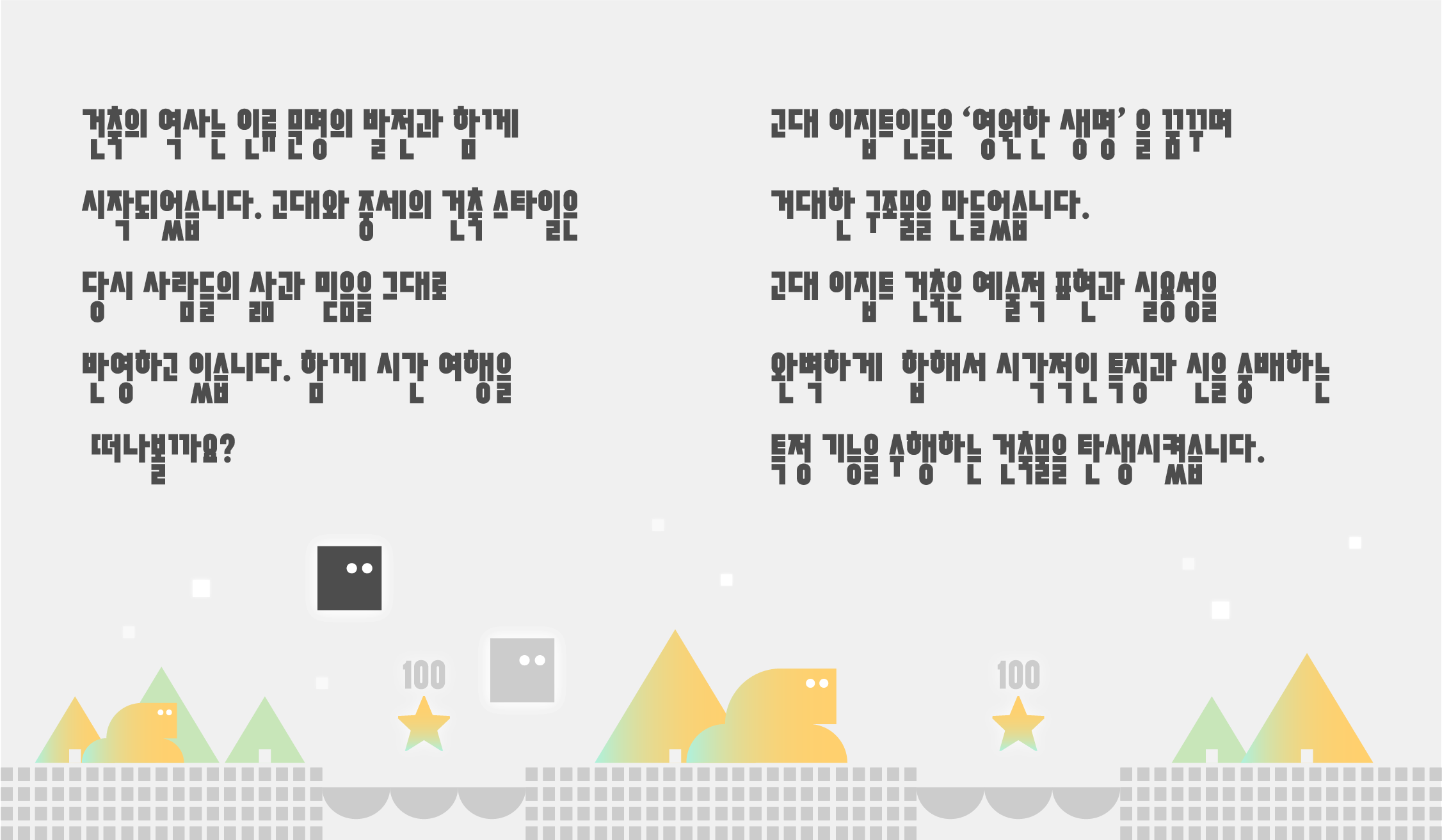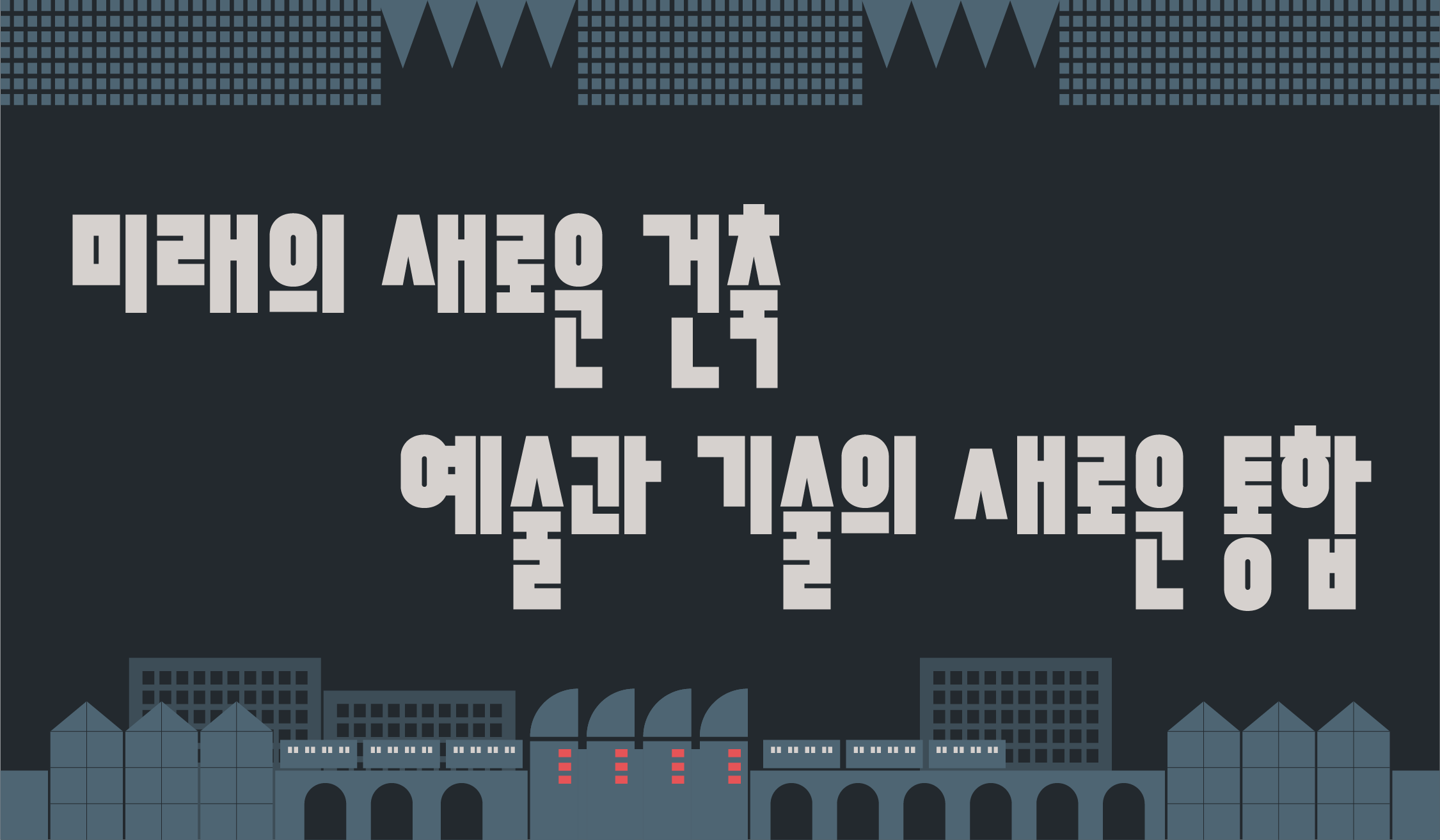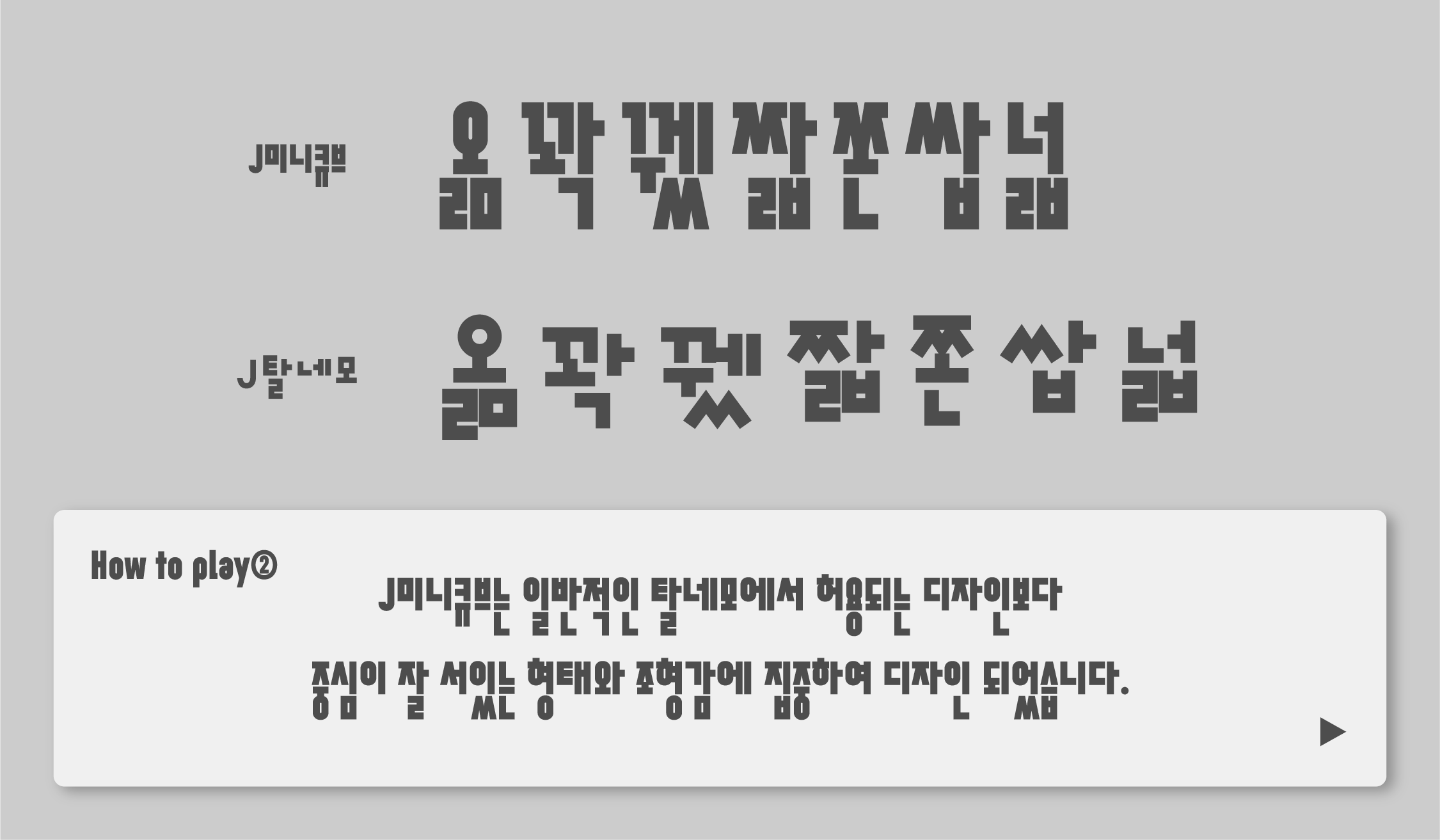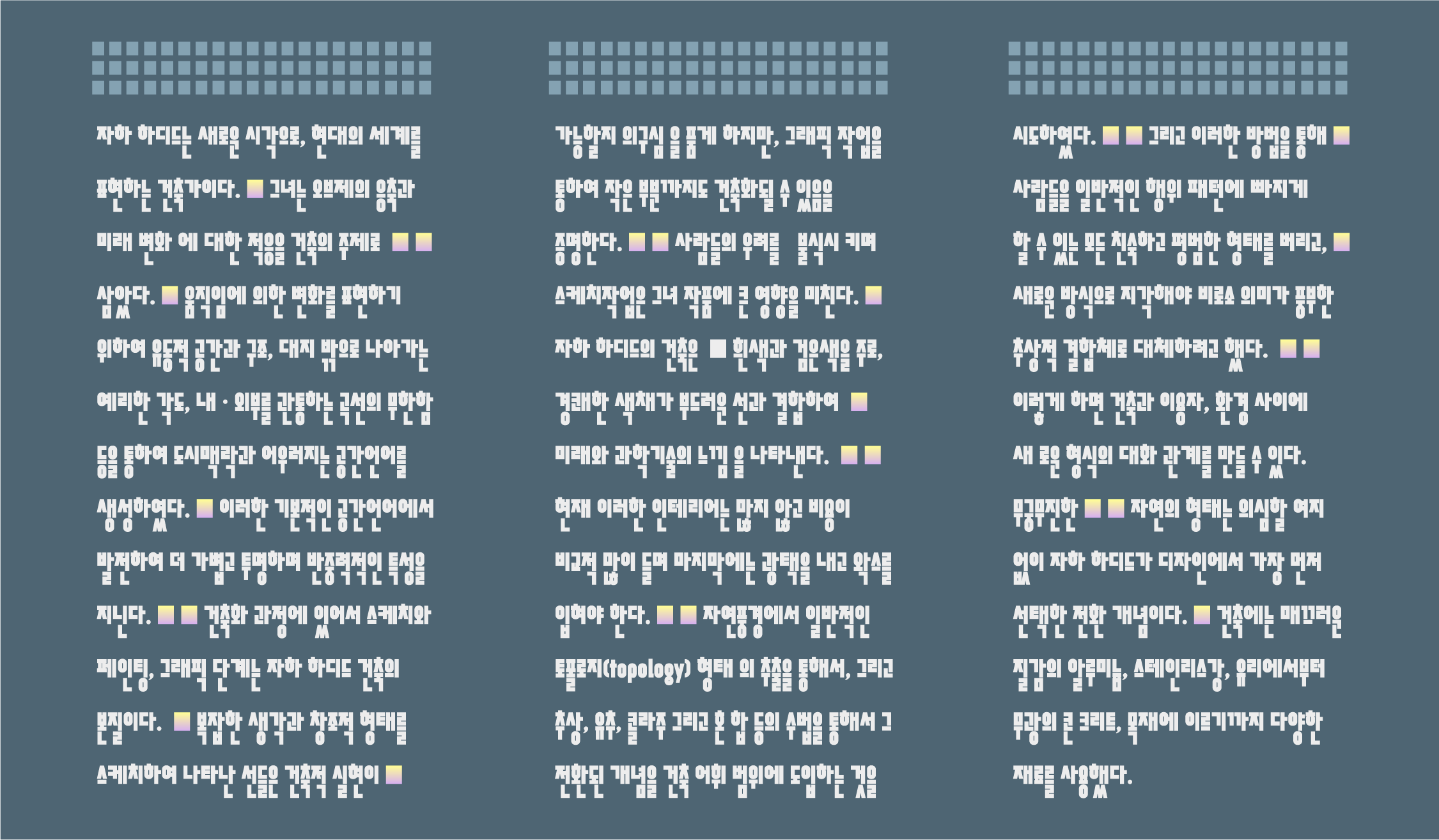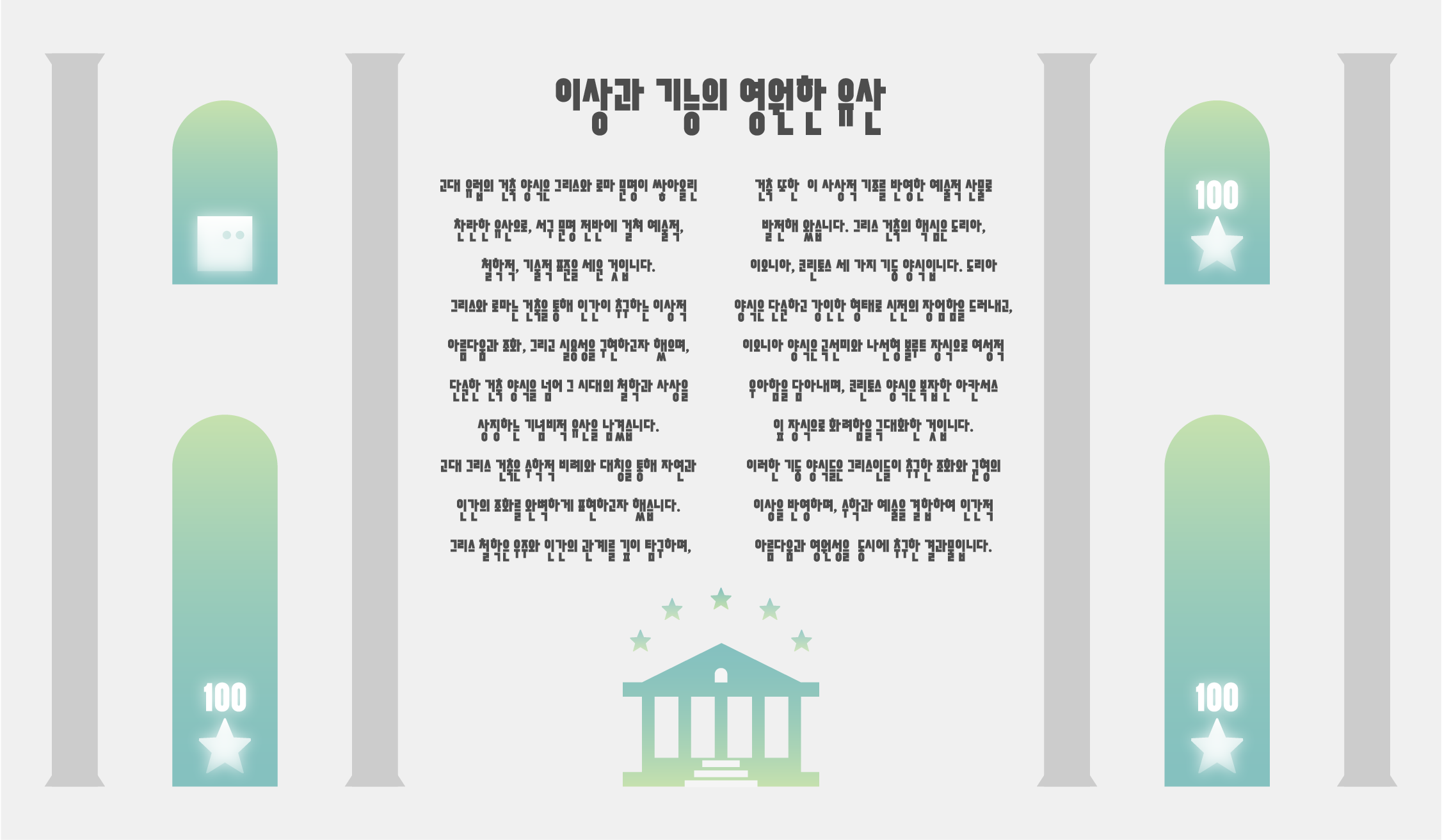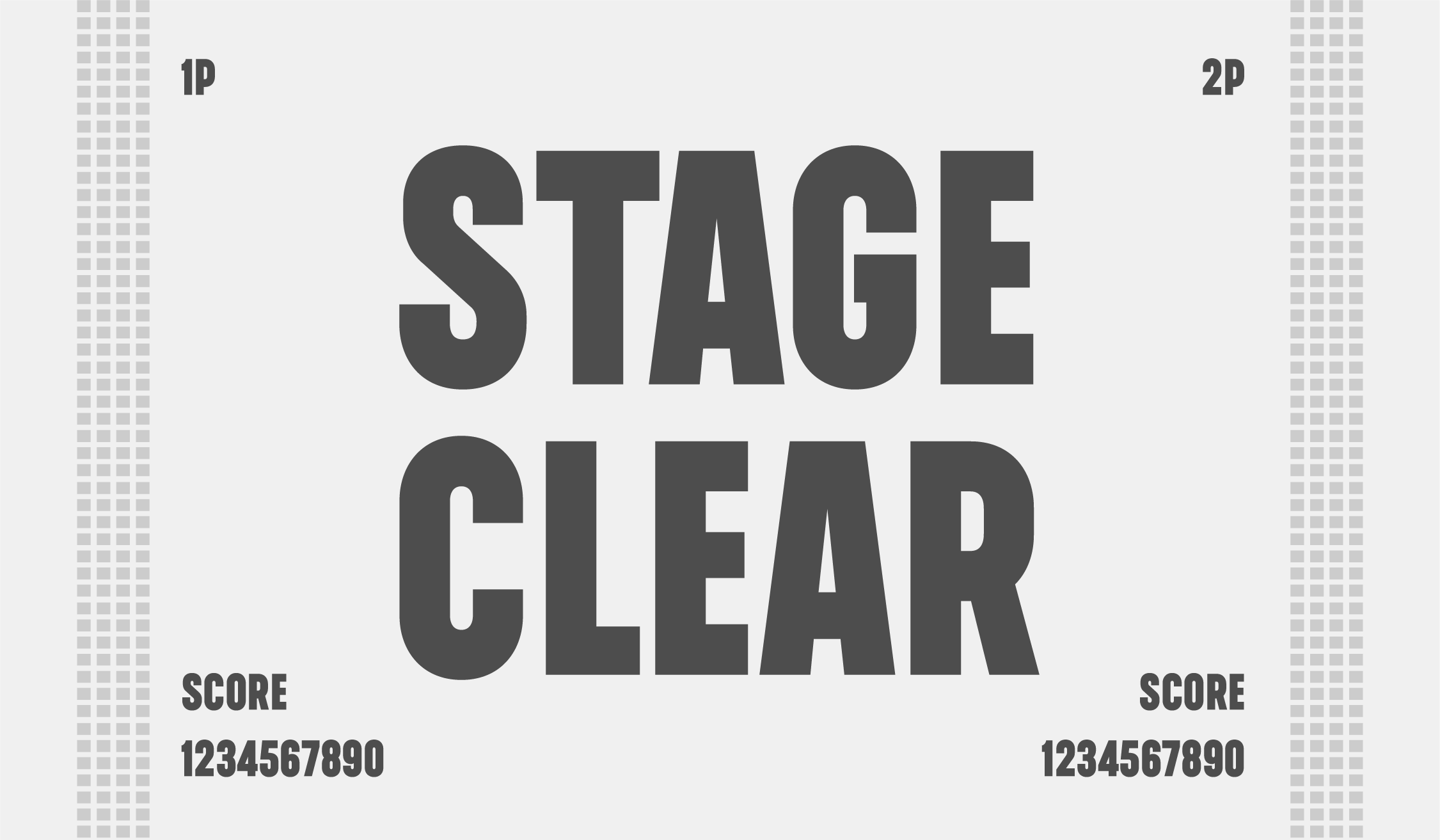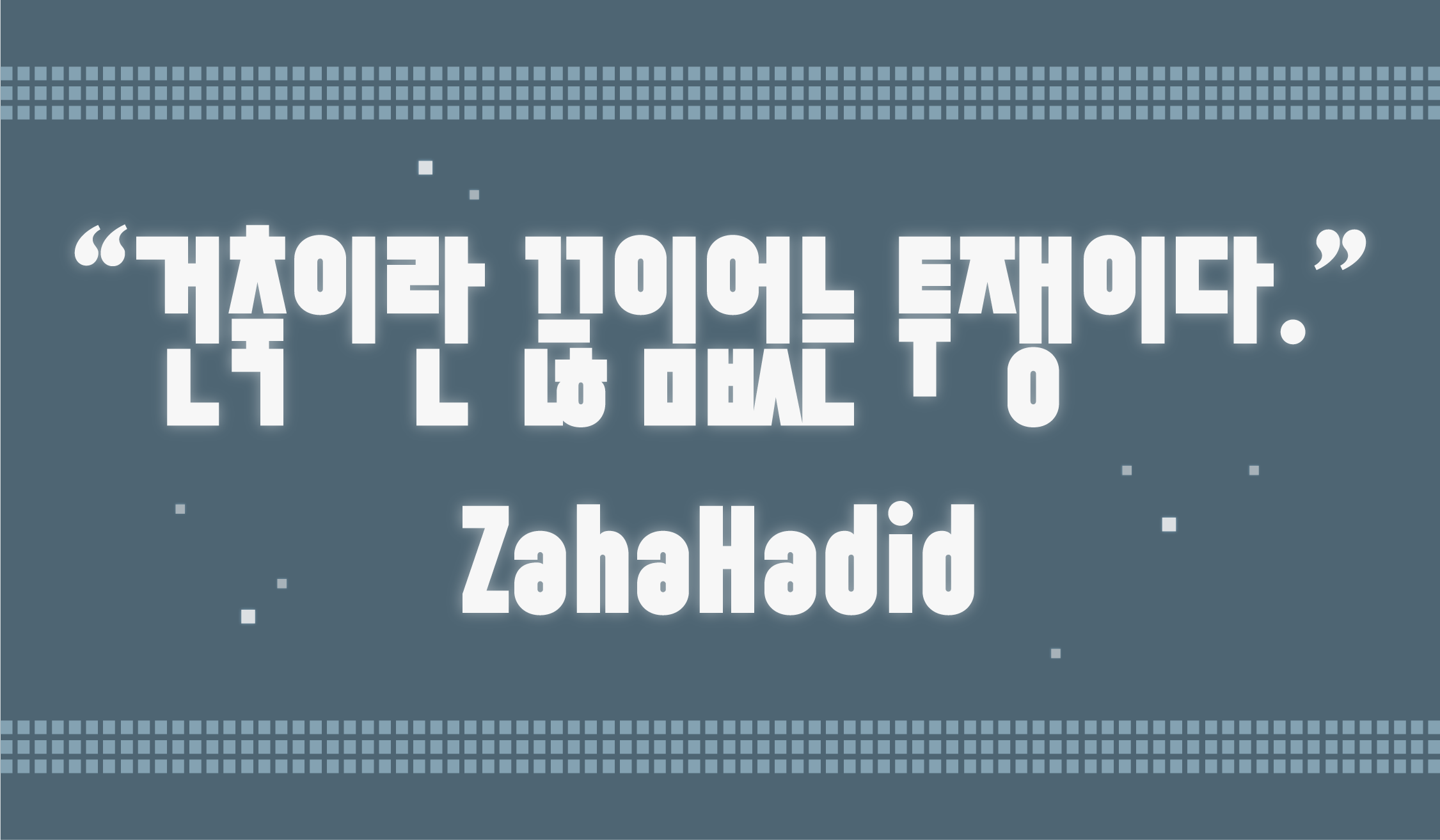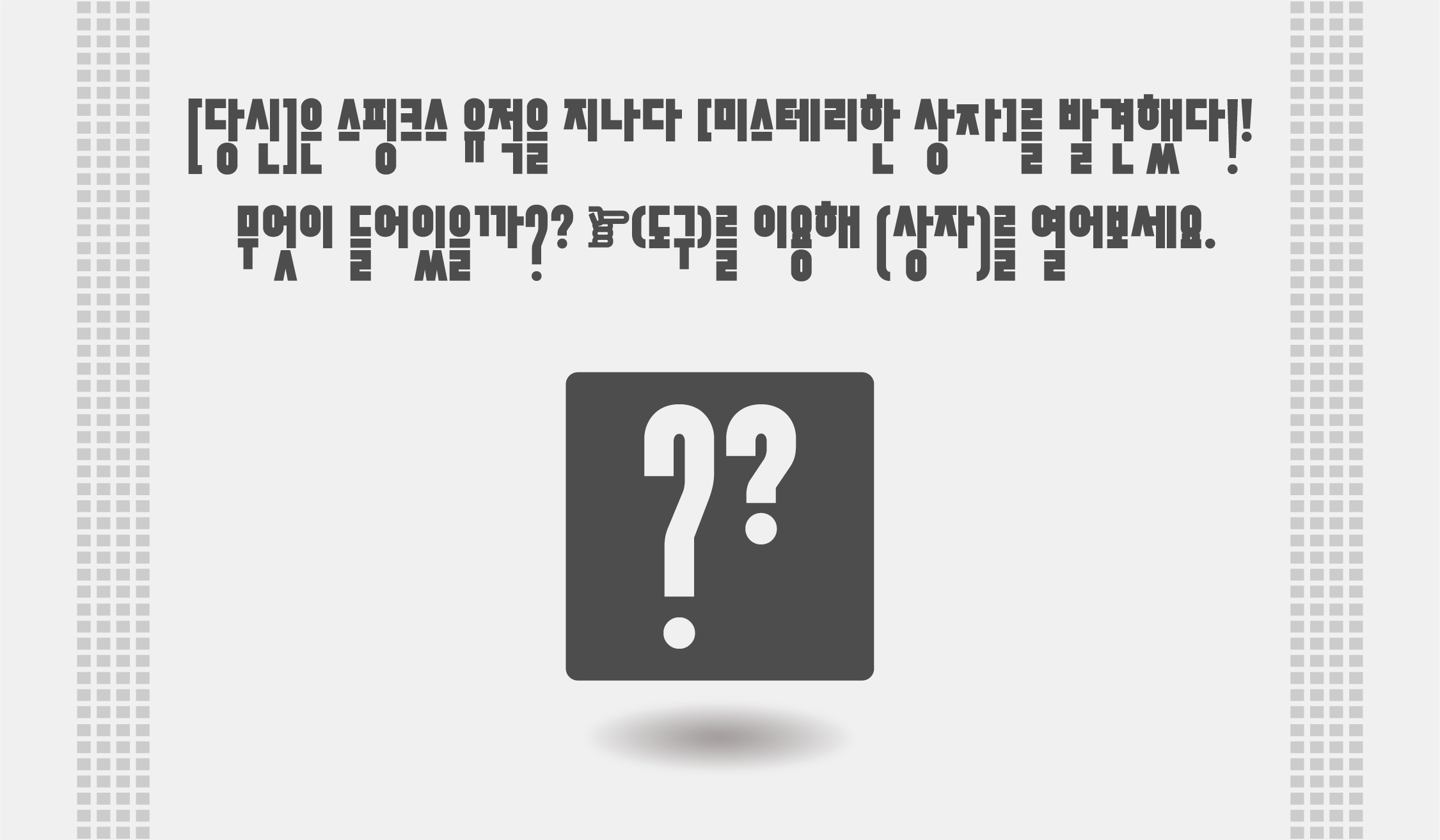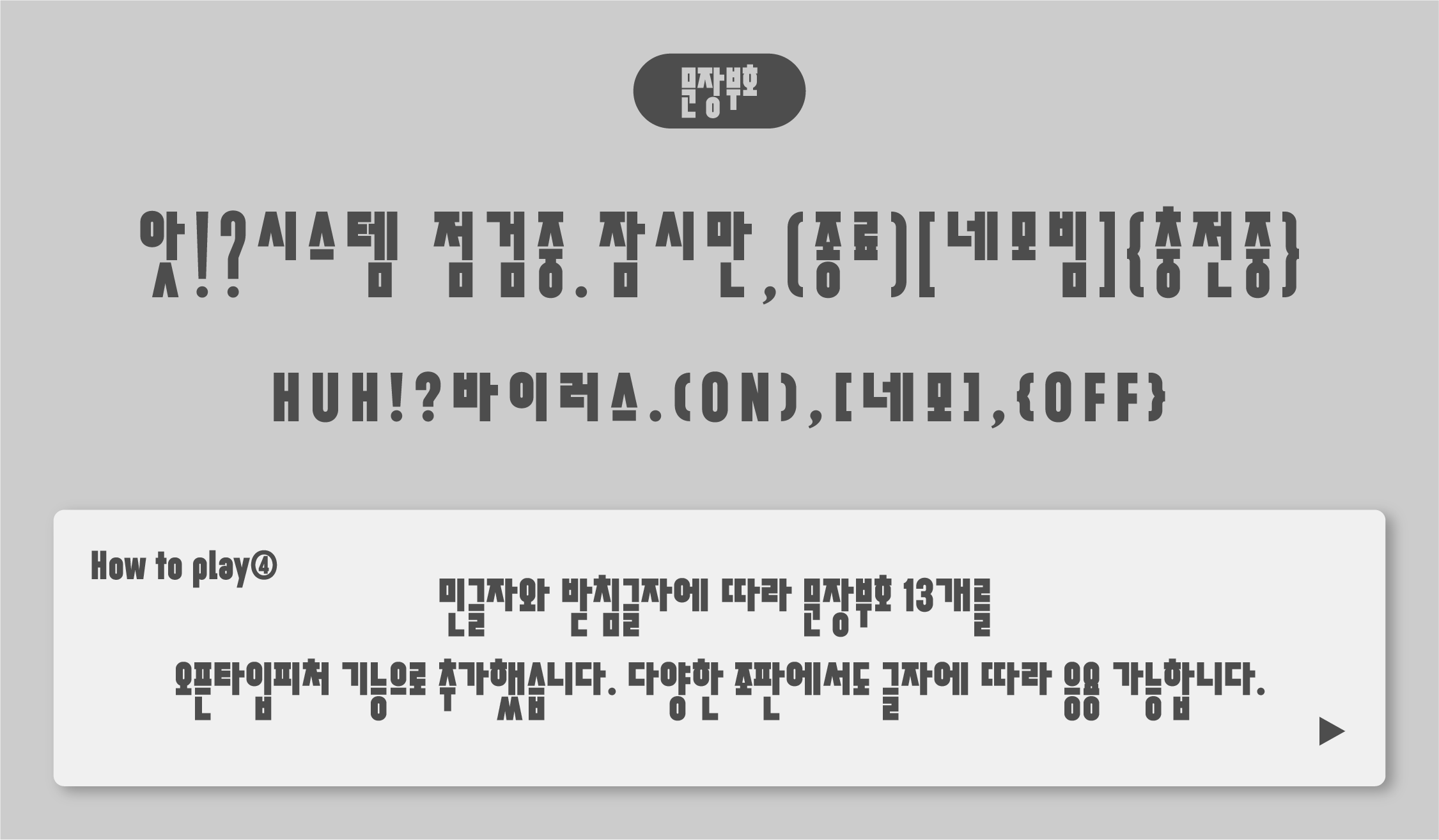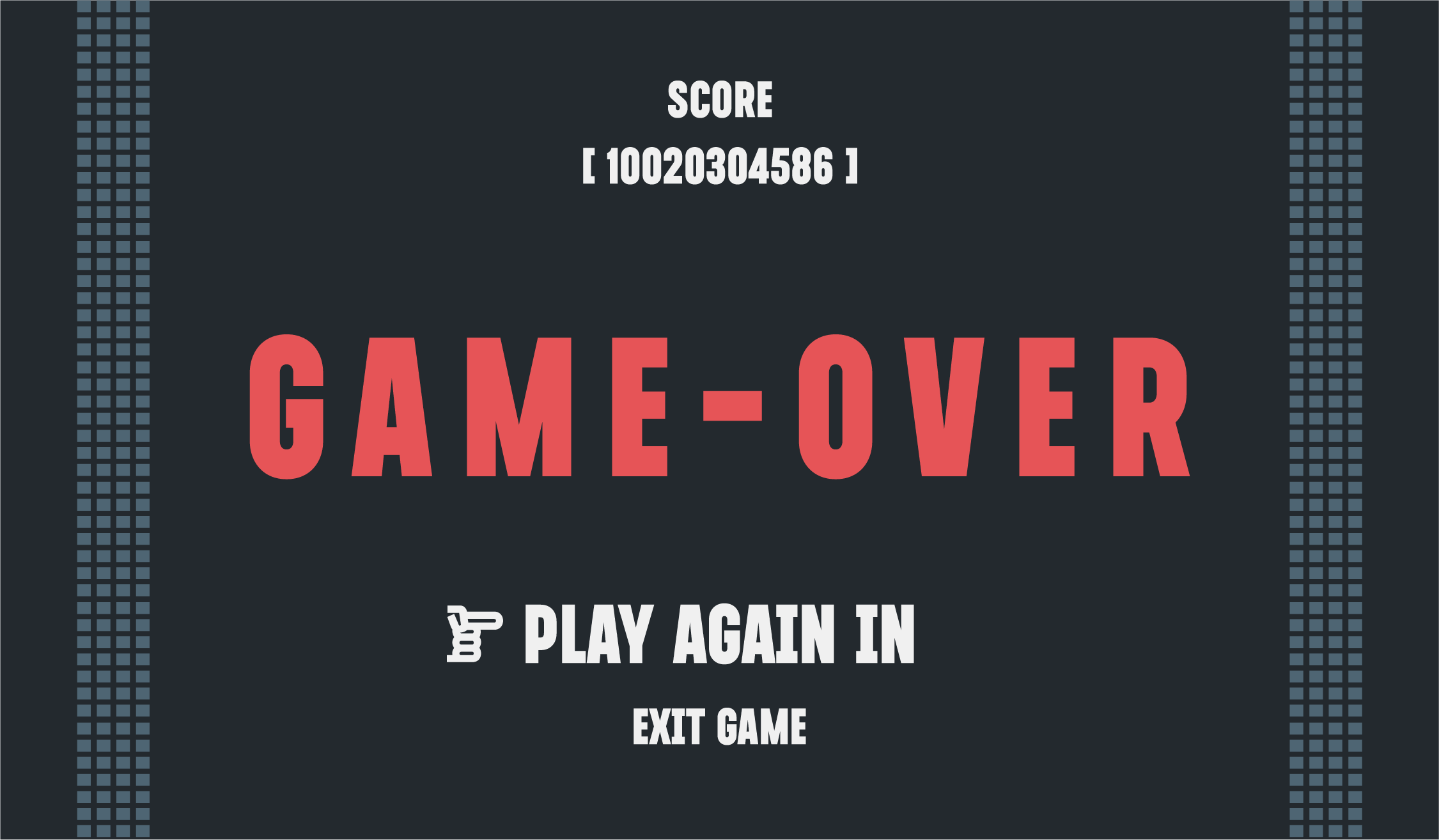
- 오픈타입 피처
민글자와 받침글자에 따른 문장부호 13자
다양한 컨셉으로 활용이 가능하고 독특한 디자인 요소가 많은 서체 시리즈. 개성있는 디테일로 시각적 재미를 더하고 풍부한 이야기를 담을 수 있는 서체이다.
폰트 설명
J미니큐브는 2004년에 출시된 J탈네모 이후, '탈네모 스타일의 제목용 서체는 어떤 모습일까?'라는 질문을 바탕으로 기획되었습니다.
한글의 기하학적 요소를 극대화하여 대칭적인 자소와 간결한 획을 통해 현대적인 형태와 인상을 전달합니다. 민글자와 받침 글자에 따라 문장부호 13자를 오픈타입 피처 기능으로 추가하여 다양한 조판에서도 글자에 따라 유연하게 활용할 수 있습니다. 또한, 가독성을 고려하여 가장 두꺼운 굵기로 제작되어 높은 주목도를 자랑합니다.
마치 글자가 들어있는 네모 상자들이 쌓여 하나의 글자가 완성되는 모습을 연상시켜, <미니큐브>라는 이름으로 출시되었습니다. J미니큐브를 통해 다양한 지면에서 시각적인 즐거움을 경험해 보세요.